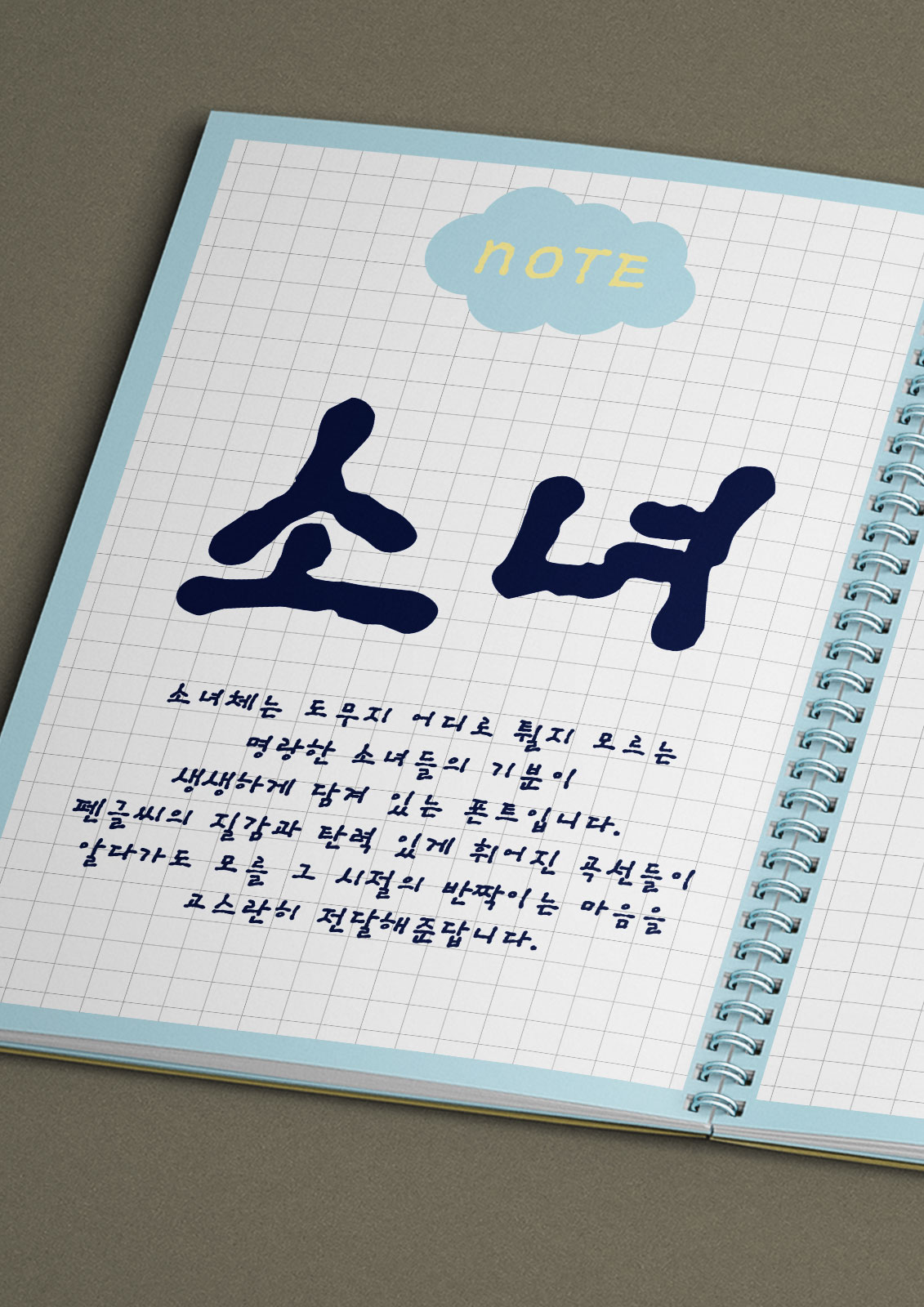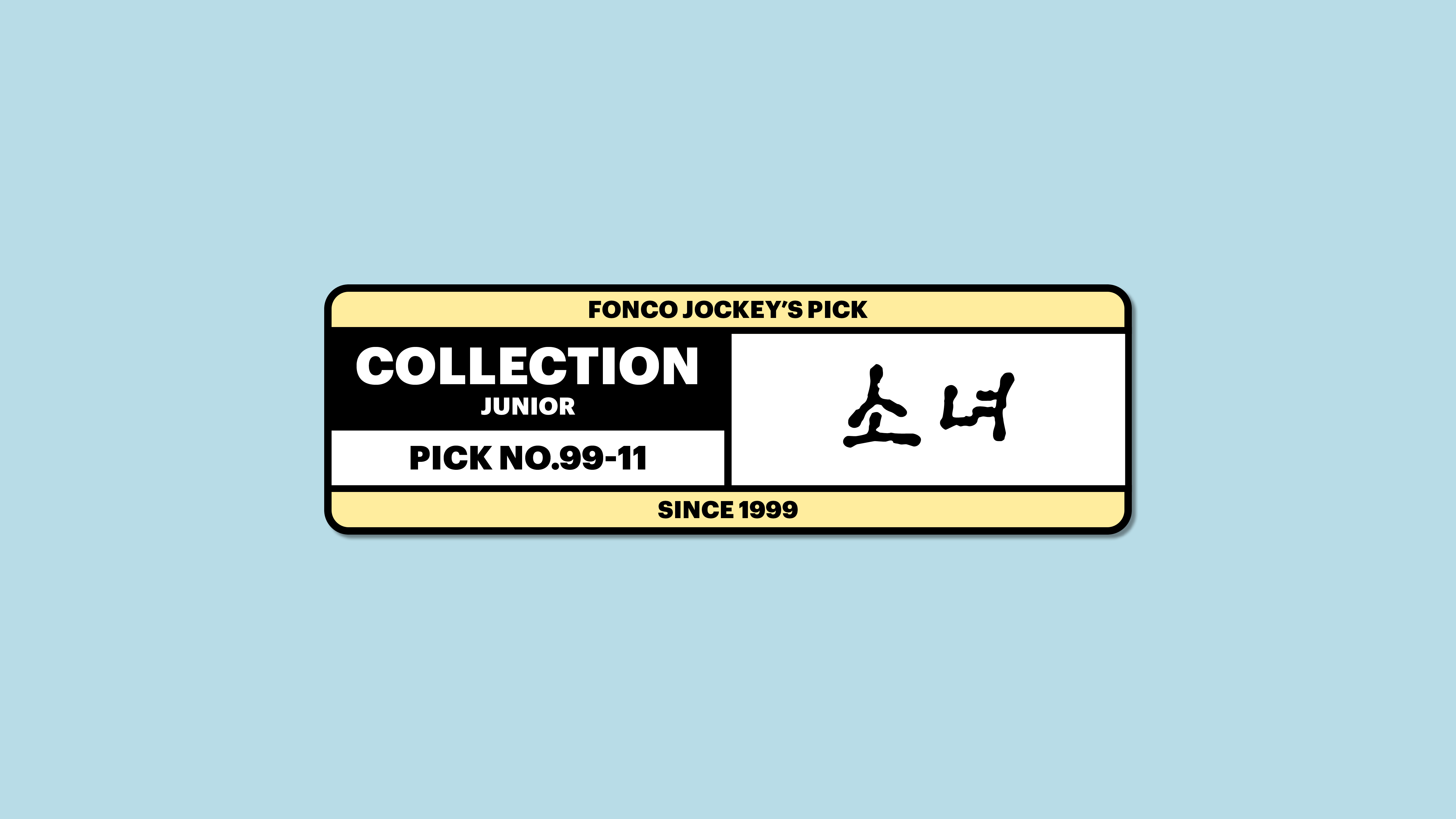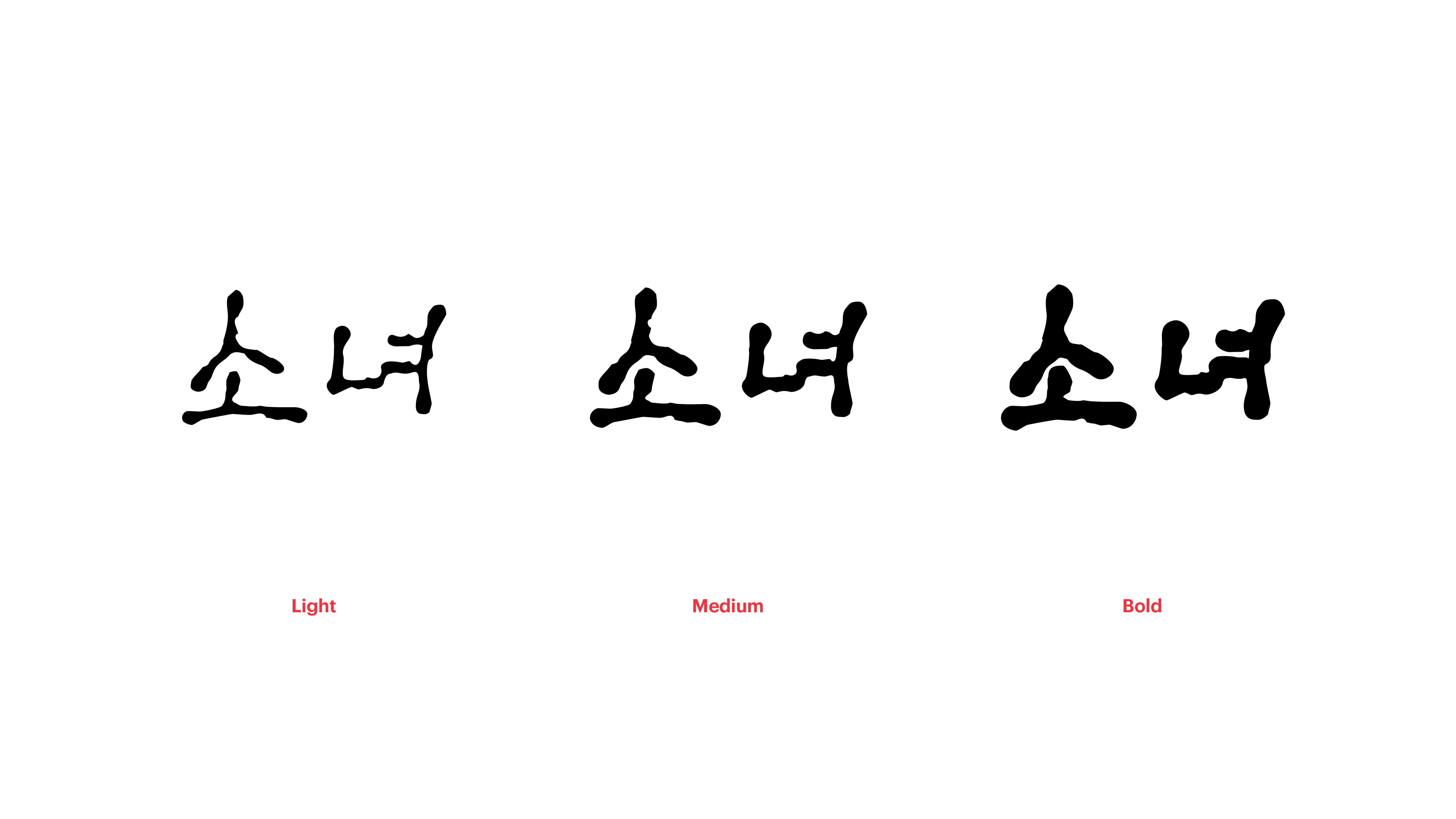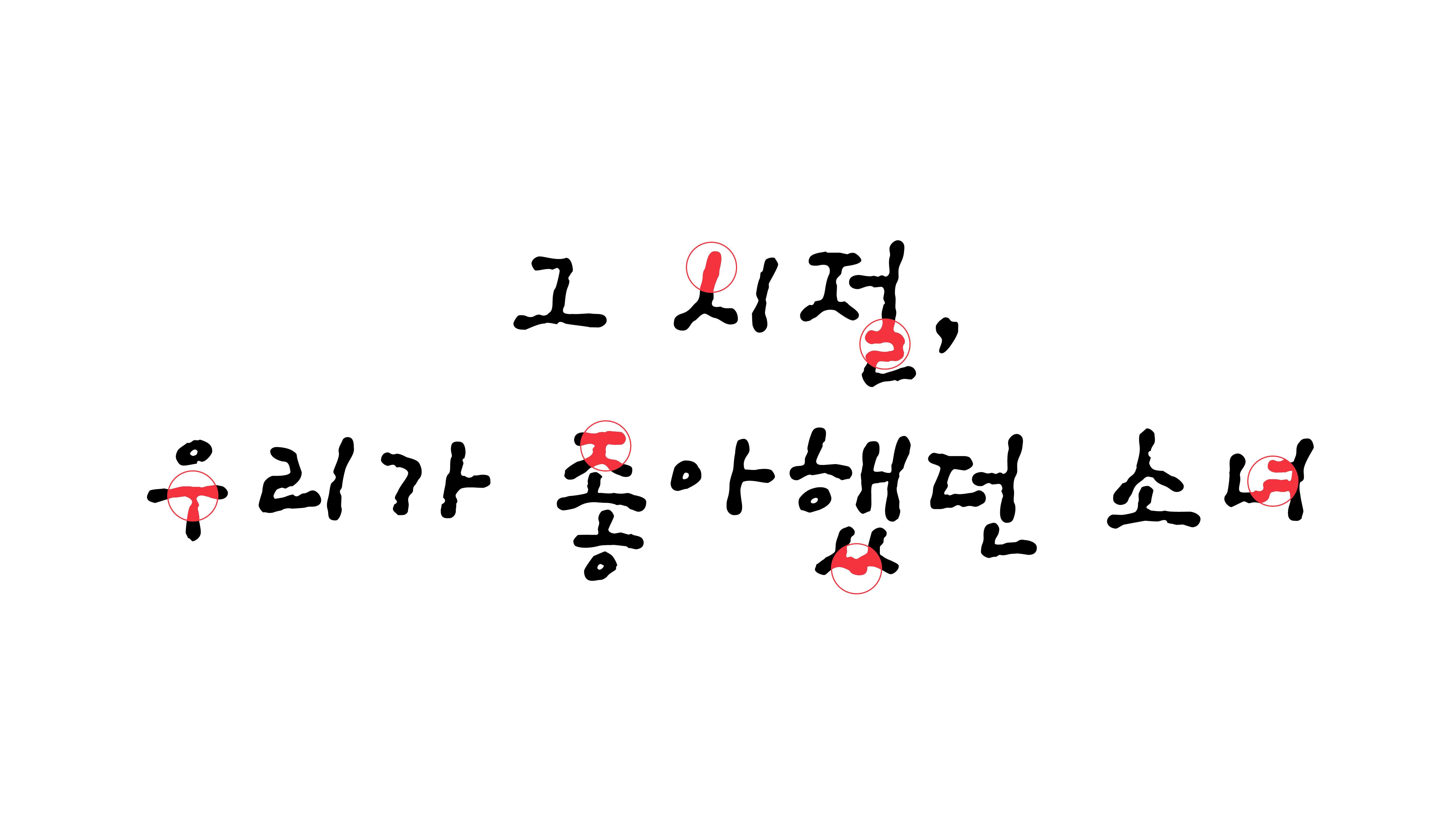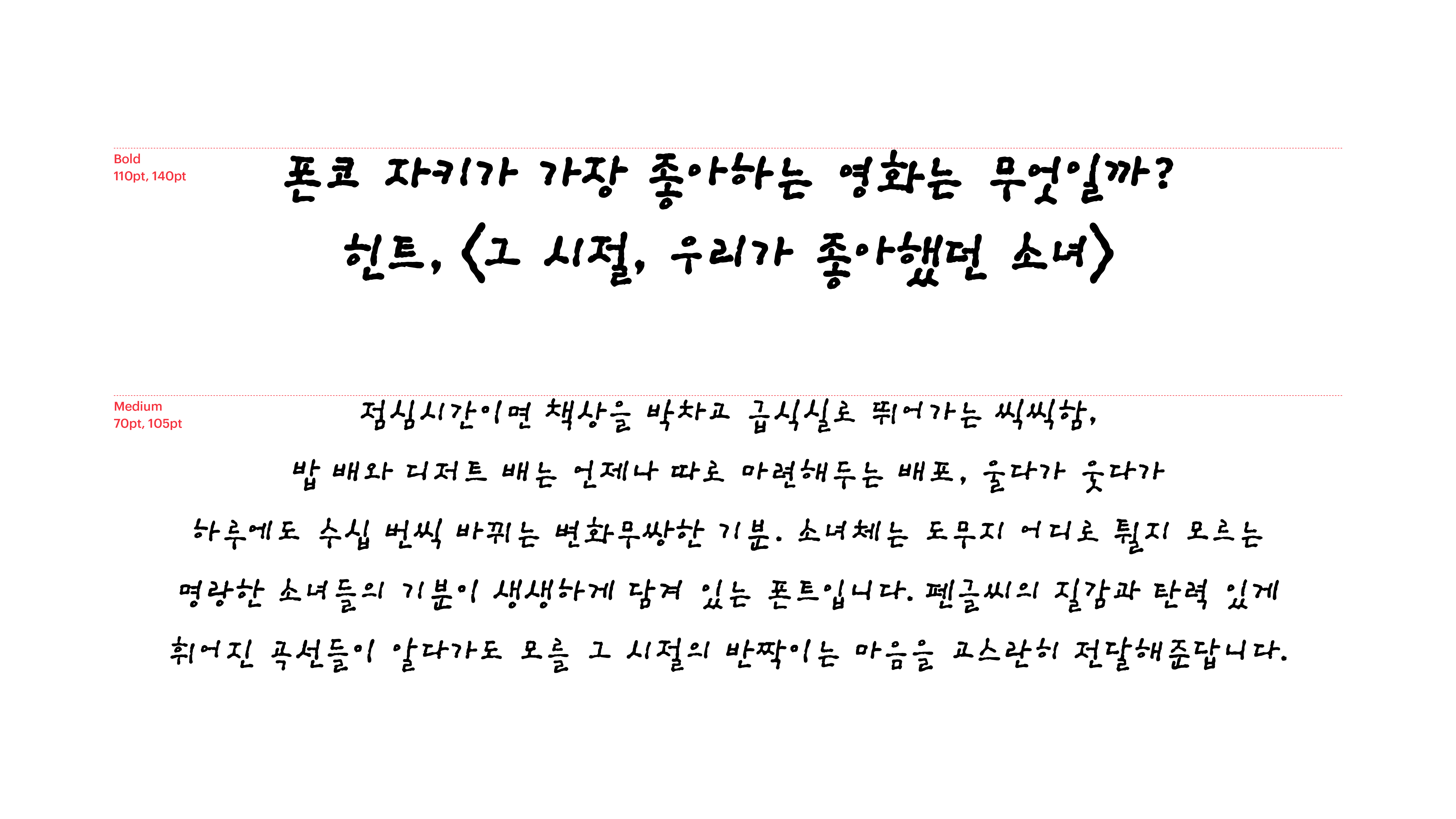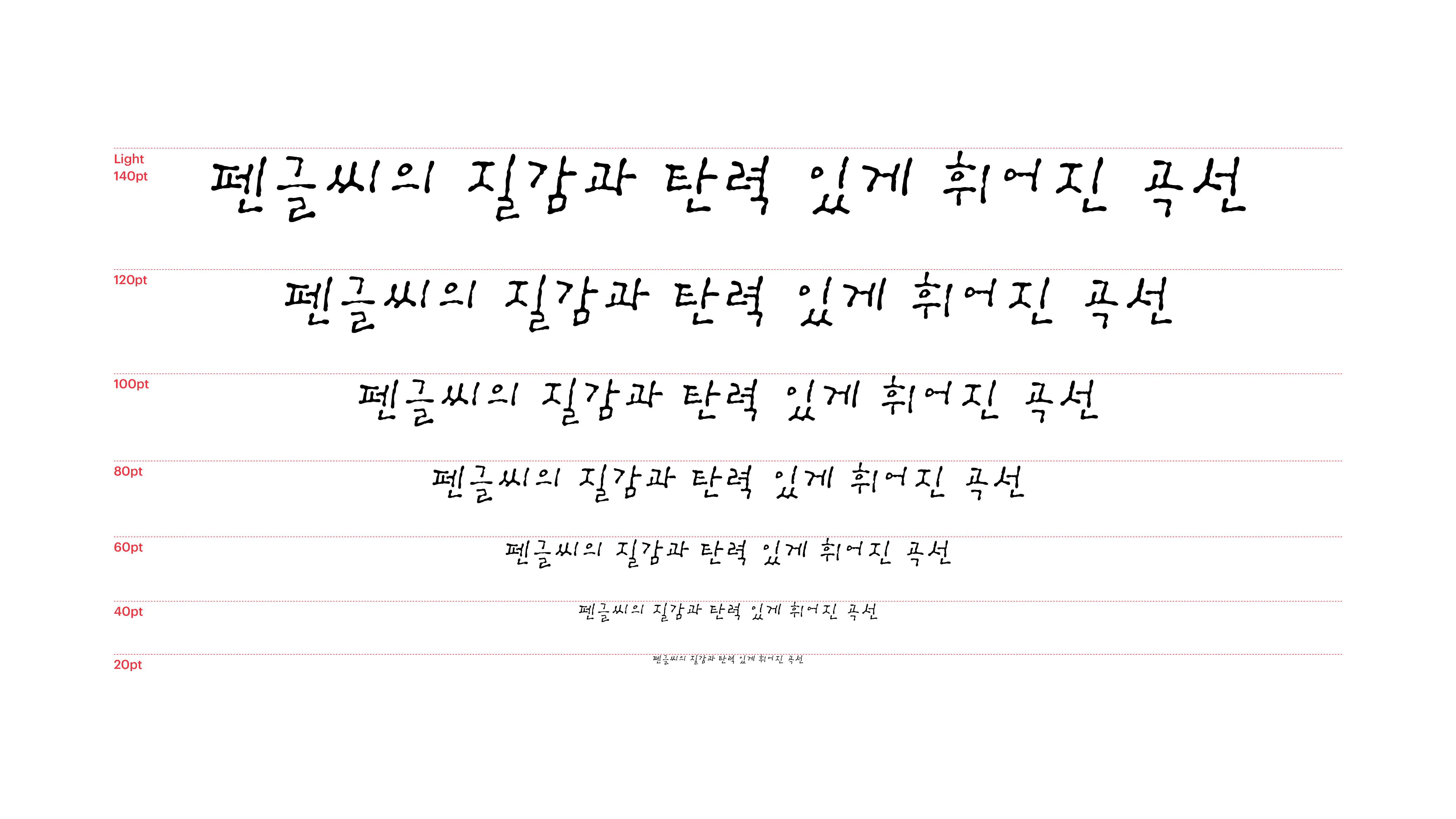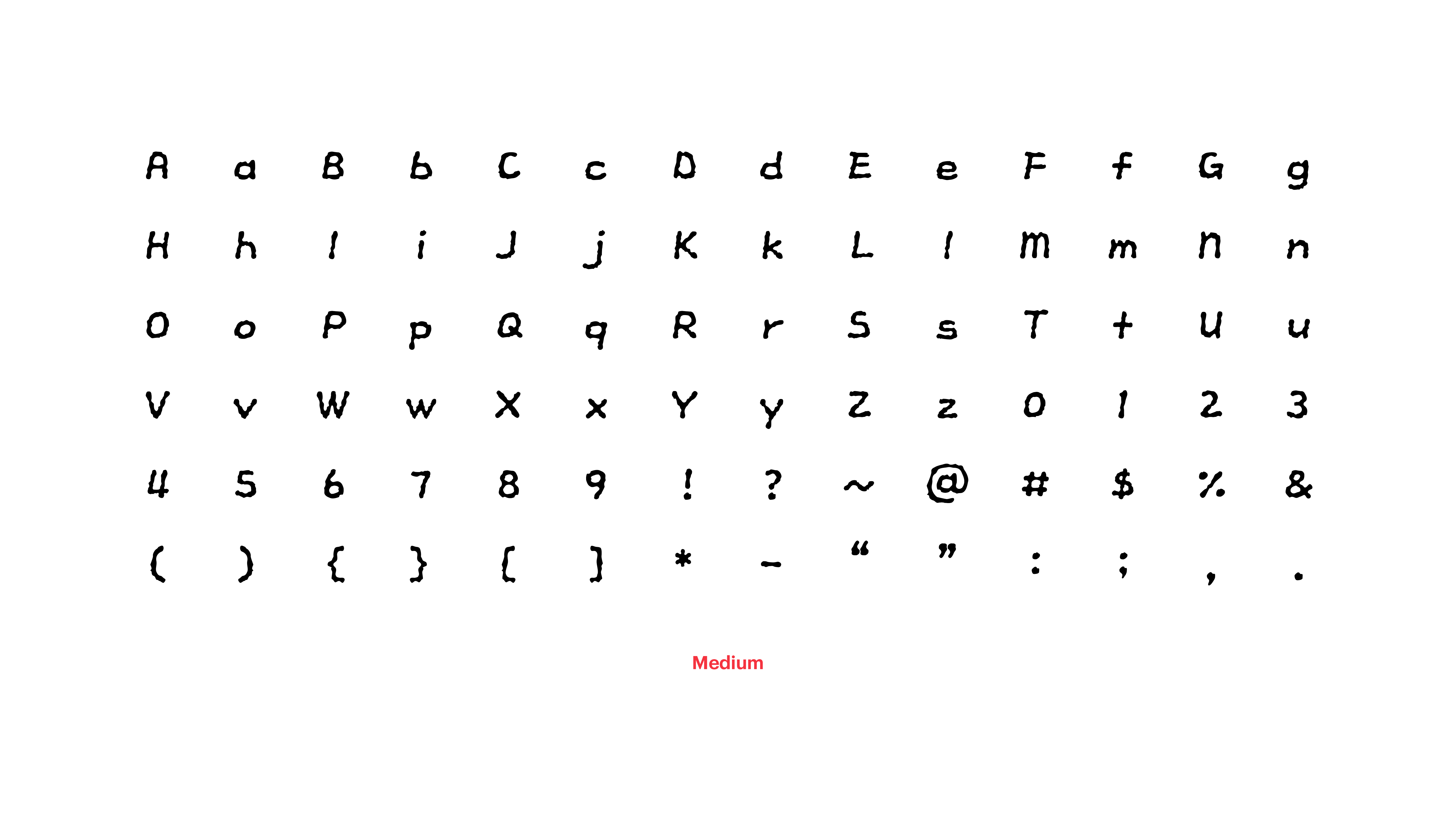
점심시간이면 책상을 박차고 급식실로 뛰어가는 씩씩함, 밥 배와 디저트 배는 언제나 따로 마련해 두는 배포, 울다가 웃다가 하루에도 수십 번씩 바뀌는 변화무쌍한 기분. 소녀체는 도무지 어디로 튈지 모르는 명랑한 소녀들의 기분이 생생하게 담겨 있는 폰트입니다. 펜글씨의 질감과 탄력 있게 휘어진 곡선들이 알다가도 모를 그 시절의 반짝이는 마음을 고스란히 전달해준답니다.
Yoon 소녀